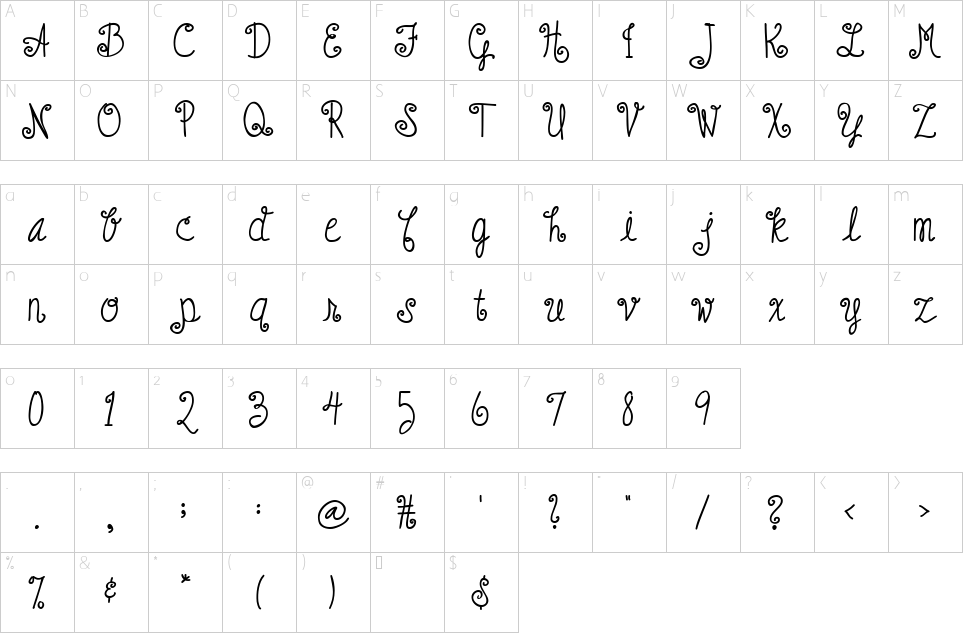
Austie Bost Bumblebee é uma elegante e versátil fonte que combina rusticidade e delicadeza em um só design. Desenhada por Austie Bost Fonts, esta fonte é perfeita para aqueles que procuram uma opção casual e confortável para seus projetos. Com seu charmoso traço, Austie Bost Bumblebee é uma excelente escolha para personalizar textos em sites, design gráfico, logotipos ou até mesmo em criações de livros e revistas. Com uma facilidade de uso e uma variedade de tamanhos, esta fonte é uma ótima escolha para um projeto em qualquer dispositivo, seja Windows ou Mac. Com apenas 9,348 downloads, Austie Bost Bumblebee se destaca como uma fonte gratuita incrivelmente versátil. Descubra por si mesmo a beleza e a elegância desta fonte e deixe seu design brilhar com Austie Bost Bumblebee.